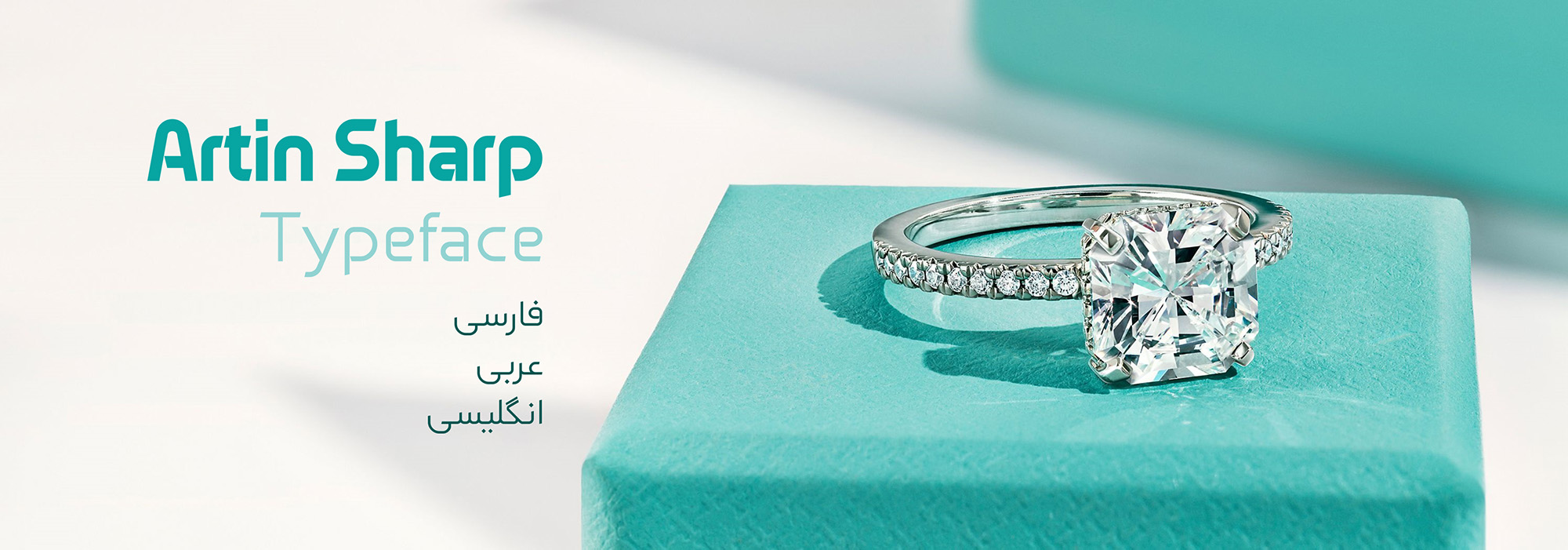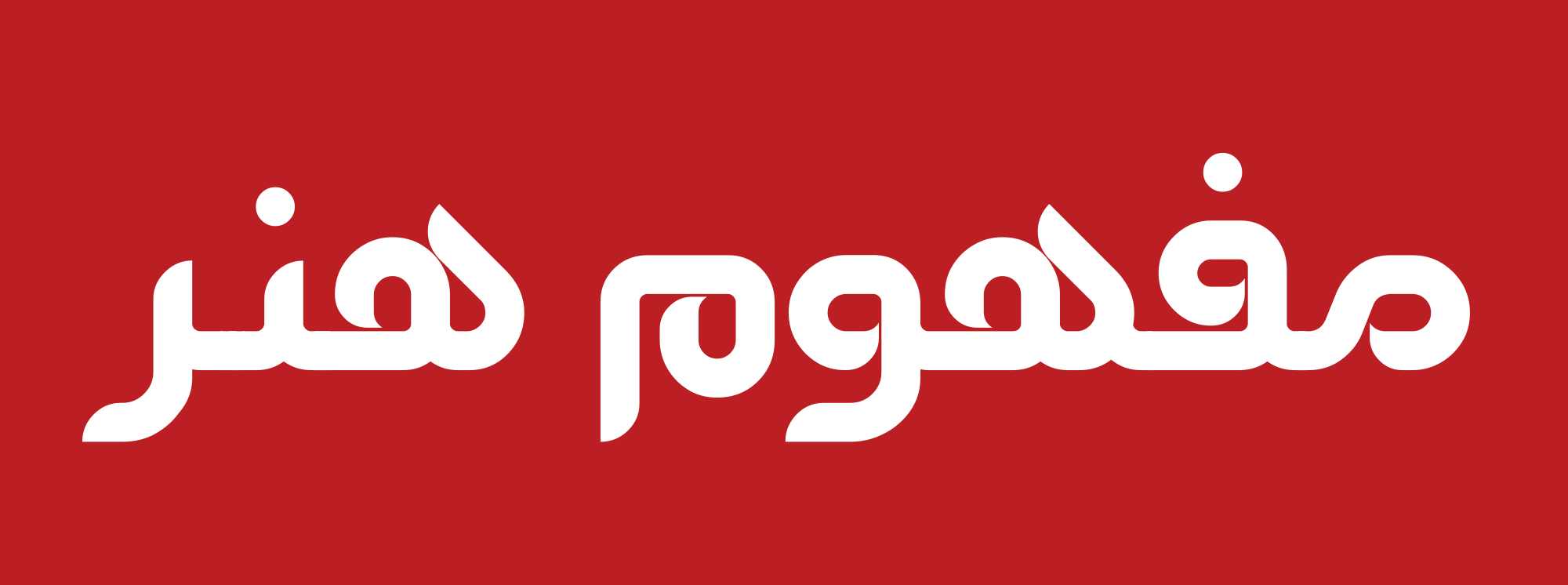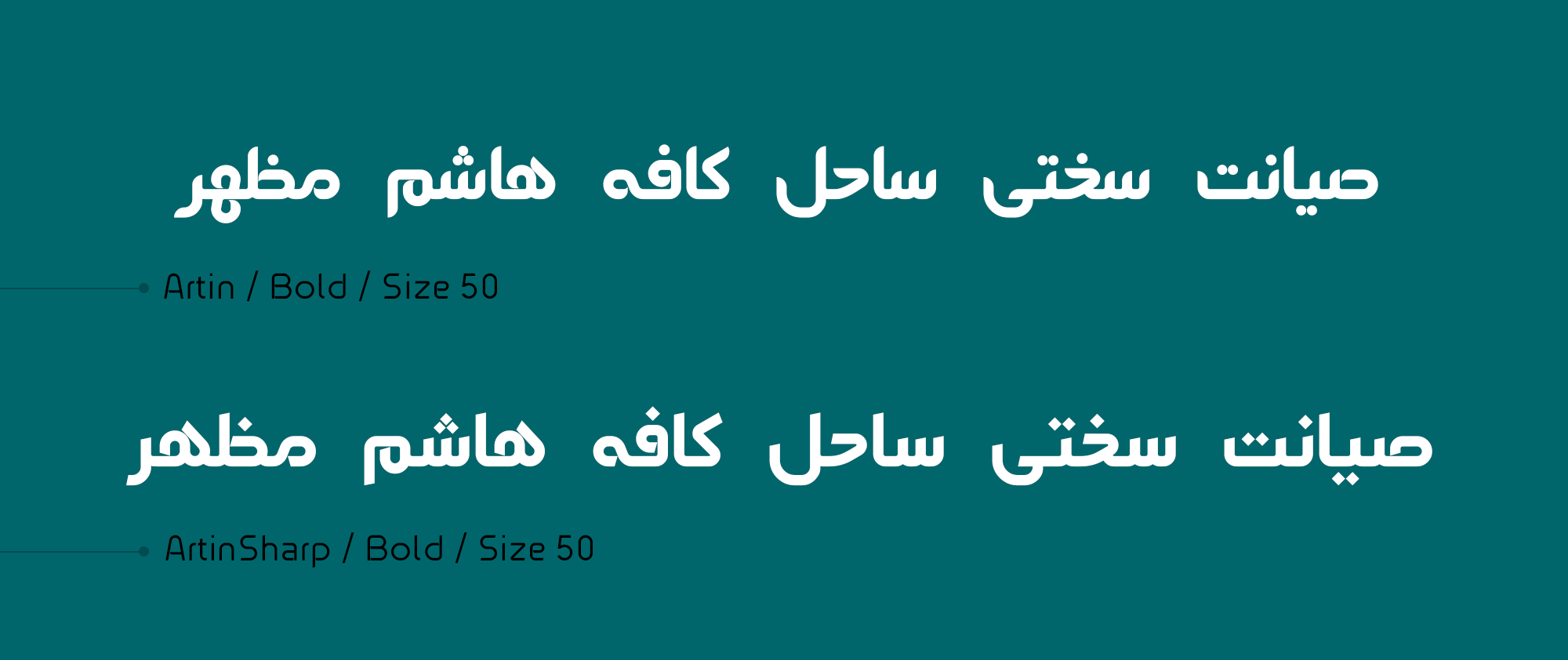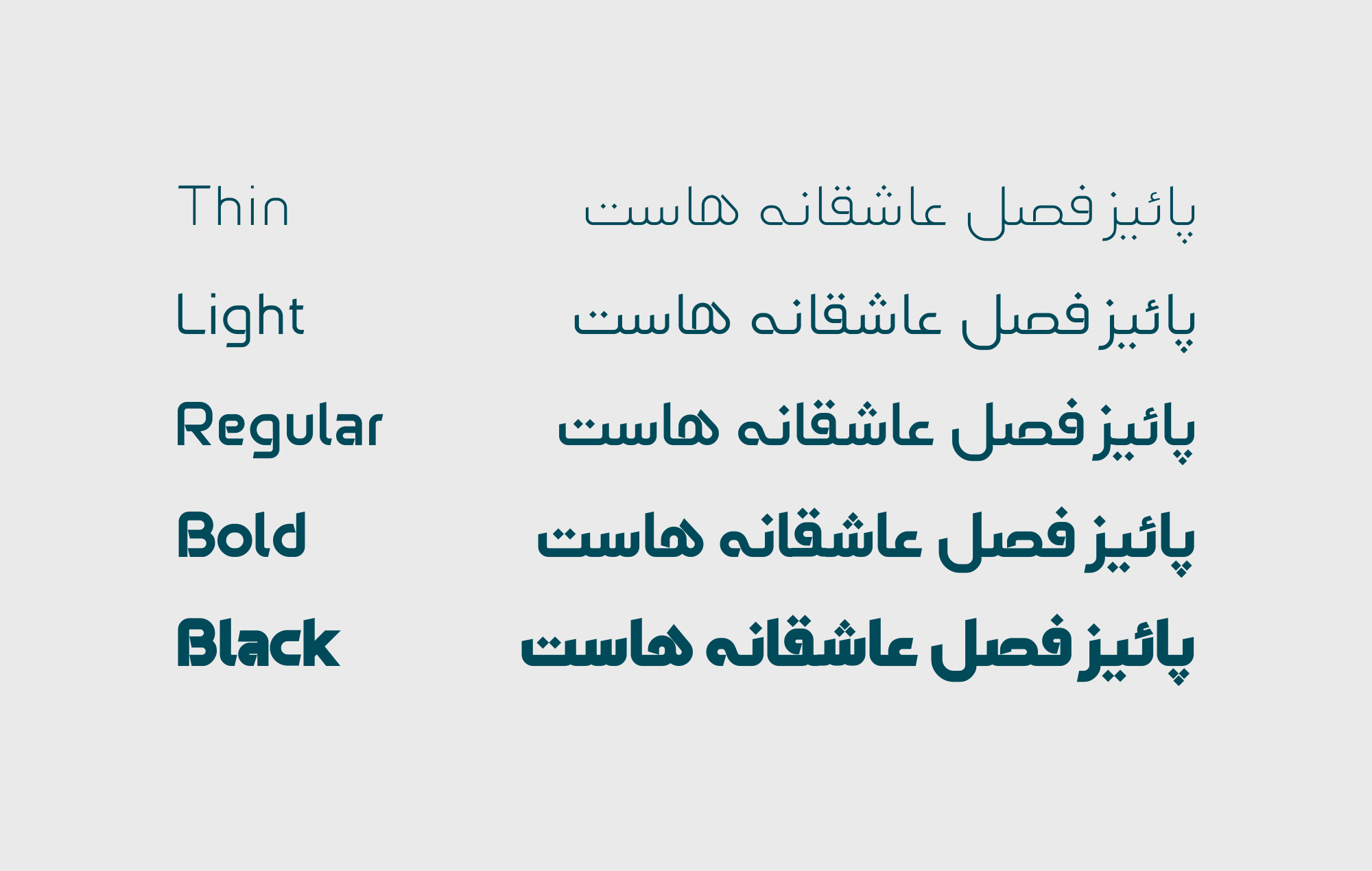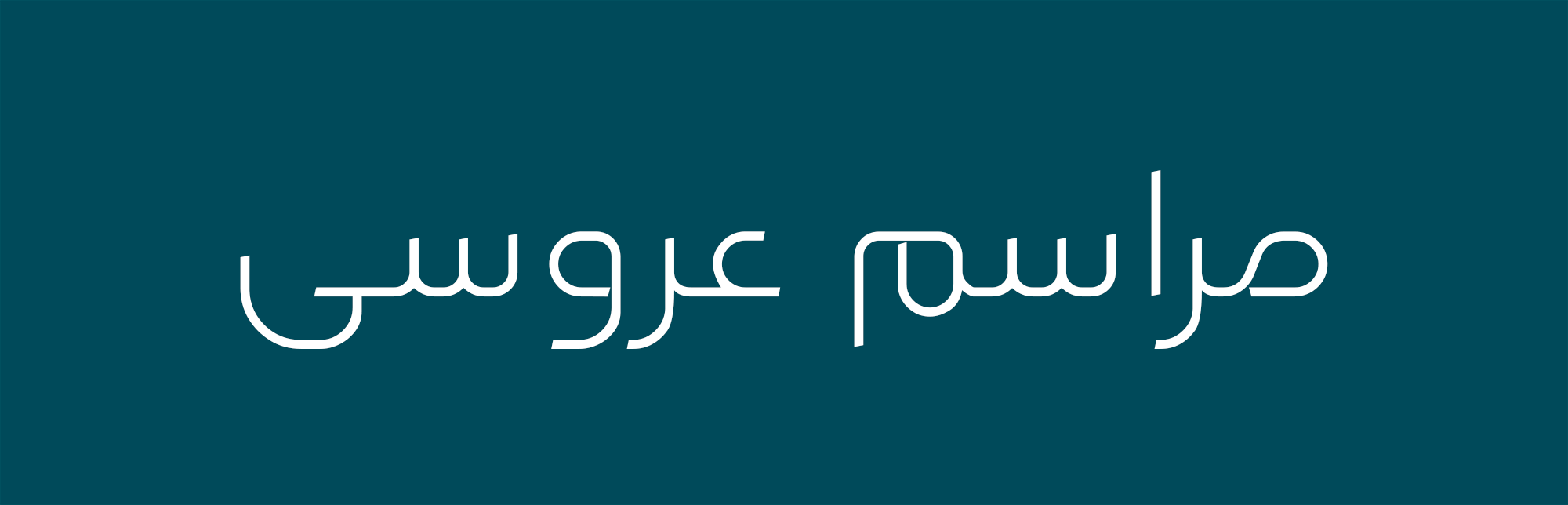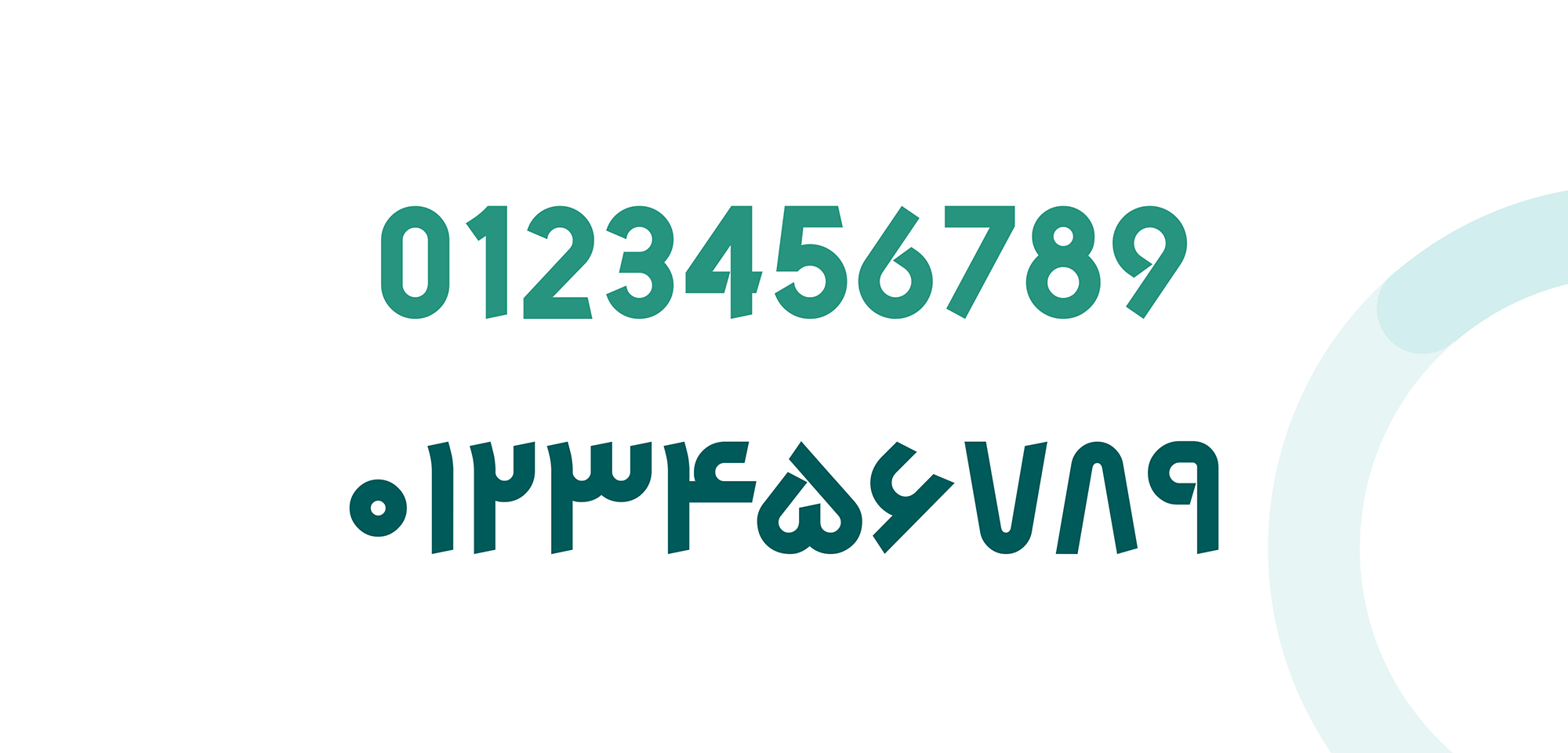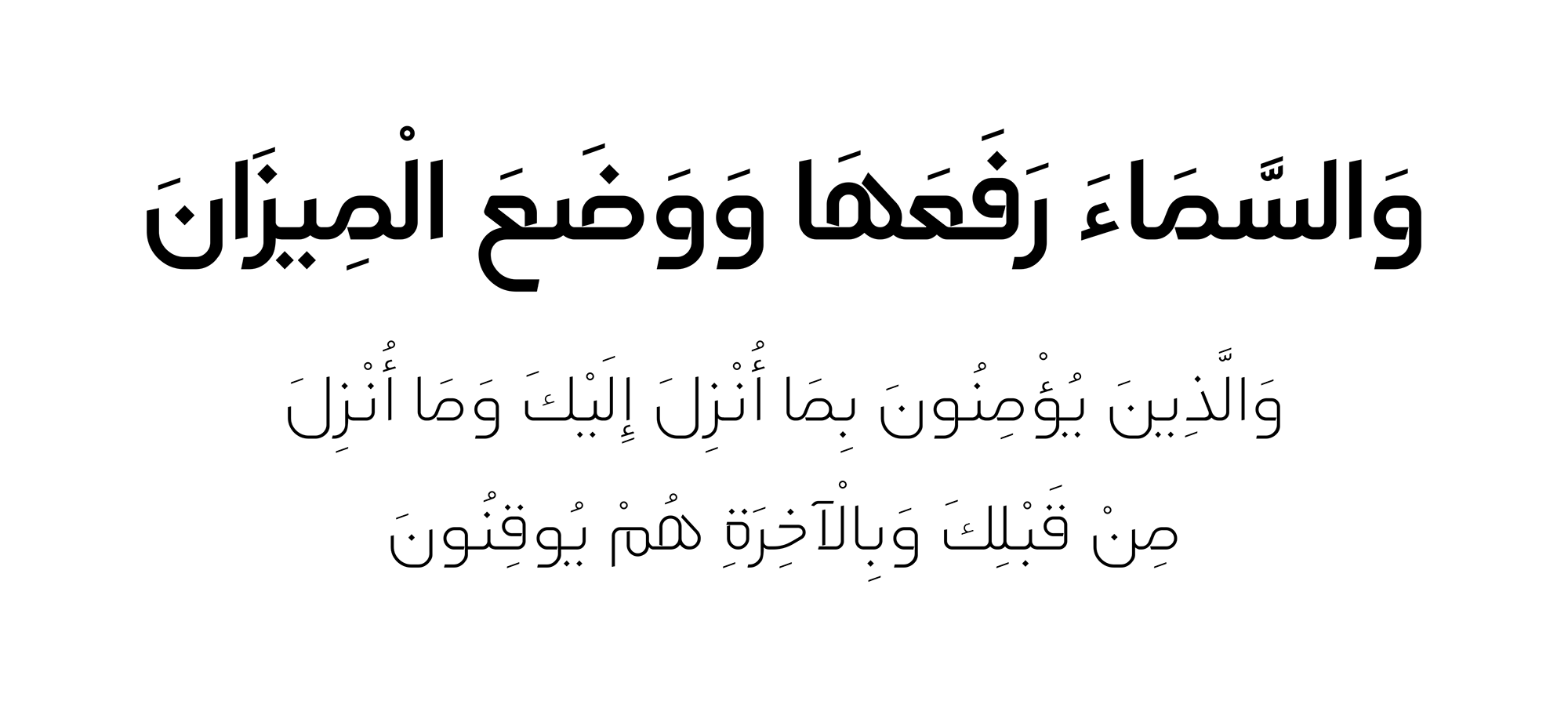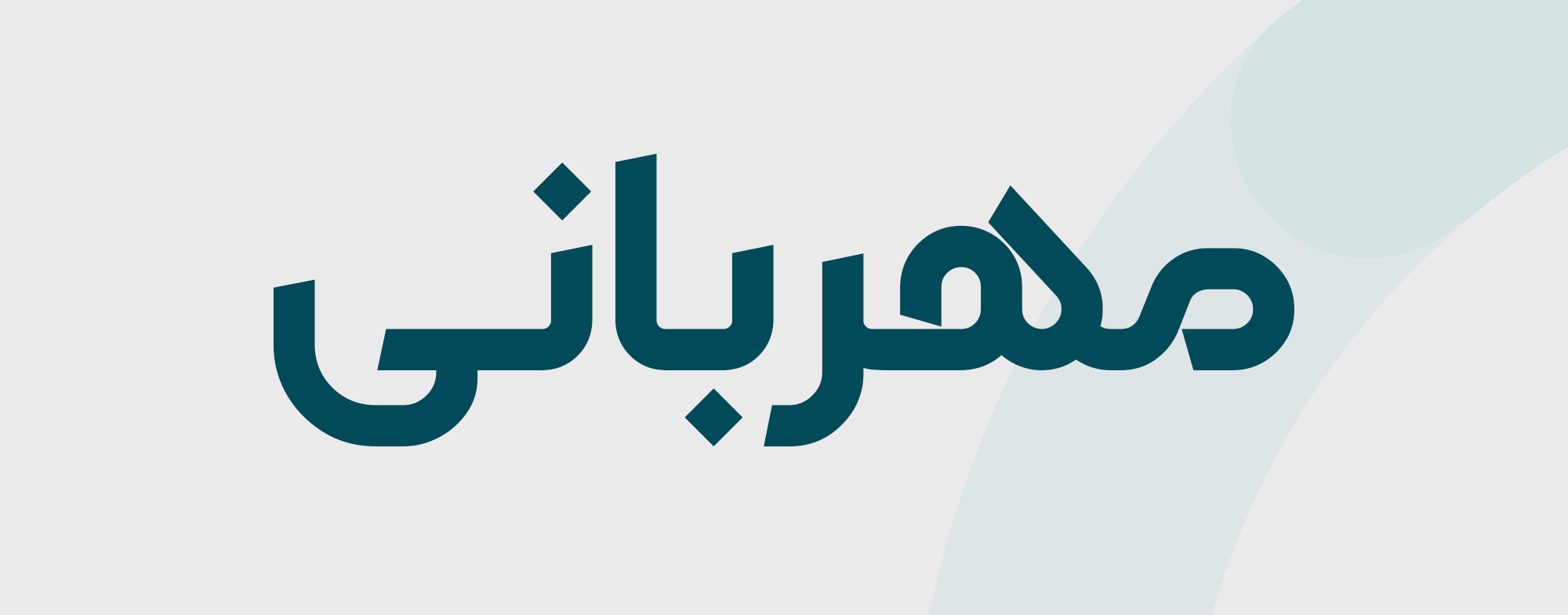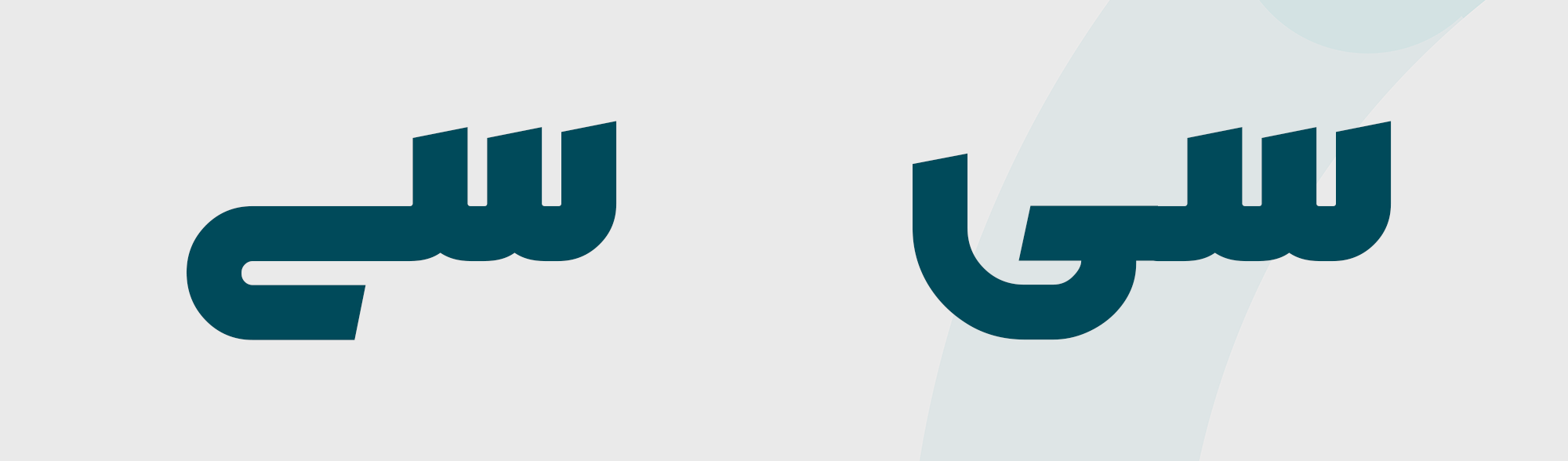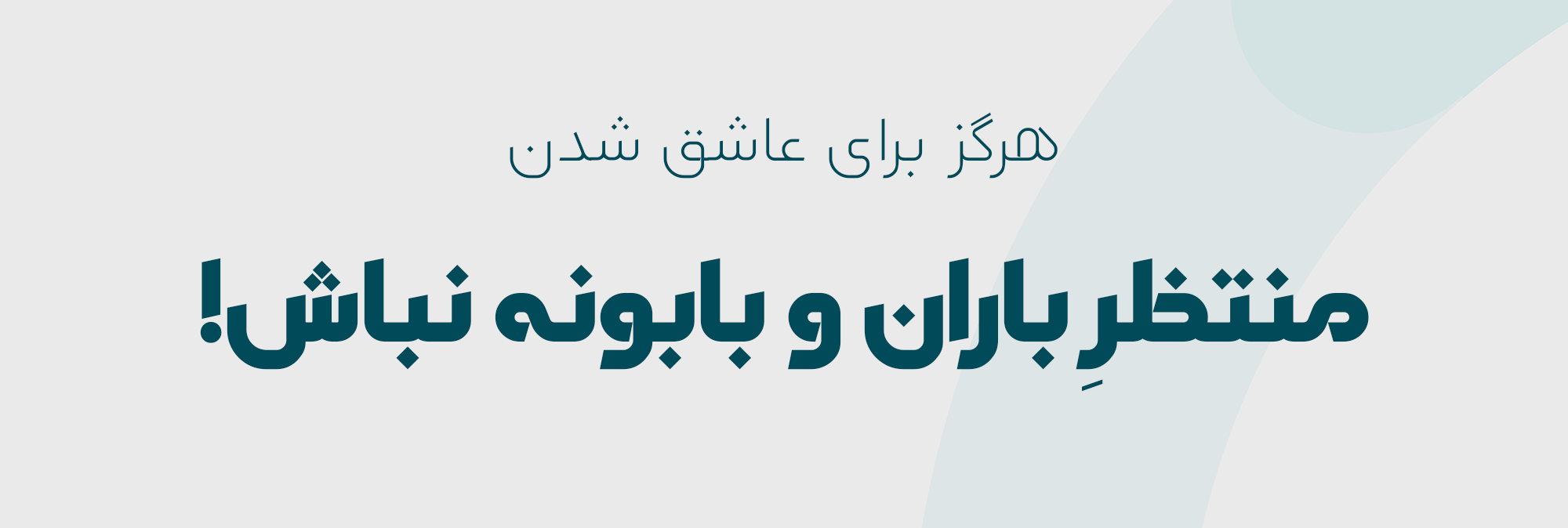
مقایسه فونت آرتین و آرتینشارپ
فونت آرتینشارپ دارای وزنهای Black, Bold, Regular, Light, Thin است.
حروف جایگزین در آرتینشارپ
حروف لاتین فونت آرتینشارپ
فونت آرتین
حروف جایگزین در فونت آرتین
برخی از تغییرات آرتین شارپ با نسخه 4.3
تغییر پیشفرض حرف ـهـ وسط
اصلاح فاصلهگذاری حرف«ر» با حروف بعد
تغییر اندازه کاراکترهای مـ و ـمـ
بازنگری در فرم و اندازه کاراکتر هـ
اضافه شدن زبان کوردی